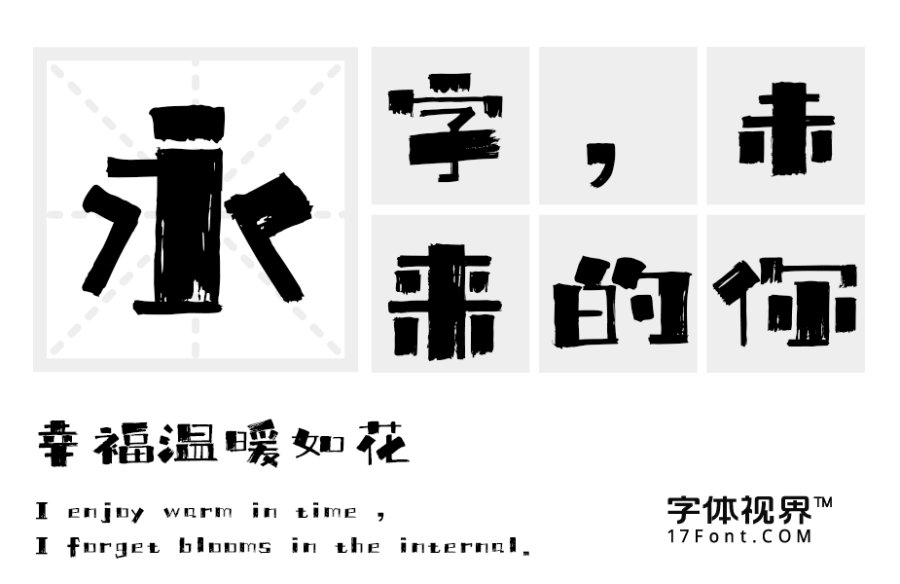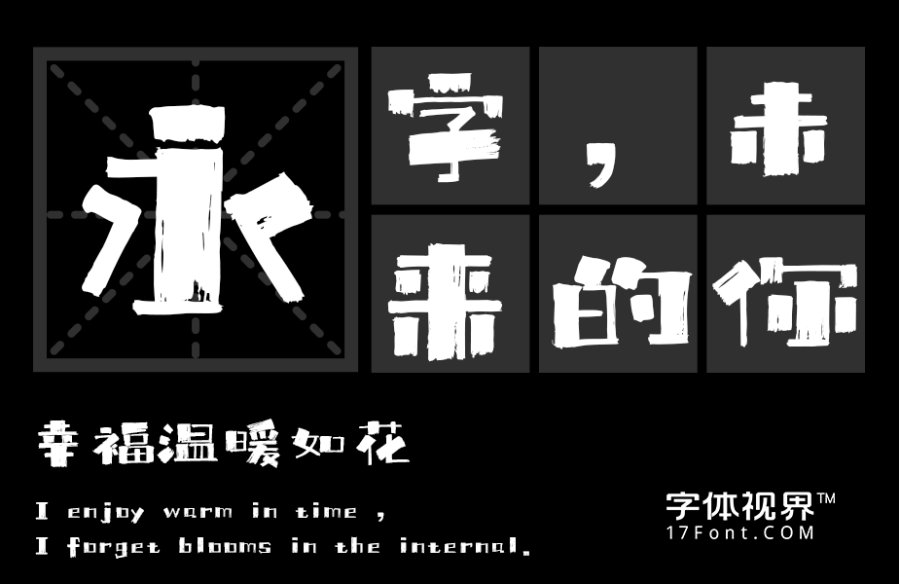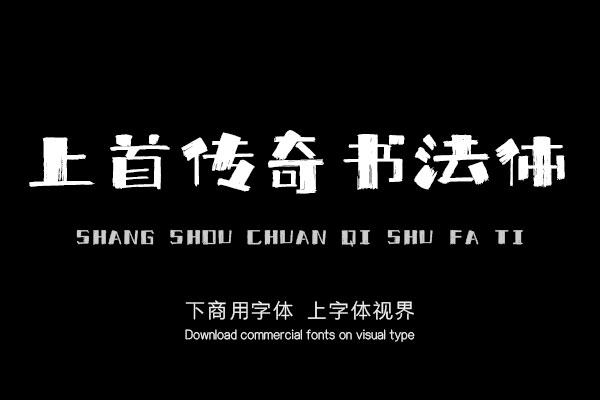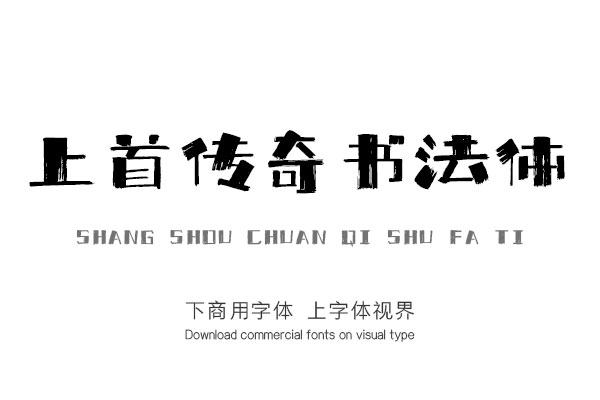
上首传奇书法体,简体中文约6763字,字体方正工整,笔刷显著,粗细变化强烈是此套字库的亮点,具有独特性。适用于搭配标志、广告标语、商业广告、正文等高端属性。购买须知:“下载服务费”与“字体VIP”所获得字体 仅用于个人非商用, 商用请联系付费授权。本字体为电脑用字,手机没有root权限不支持直接手机换字(手机如何root,请自行百度搜索教程)。购买前请先 了解清楚后再付款 ,字体为虚拟产品无法回收 一旦购买不支持退款。